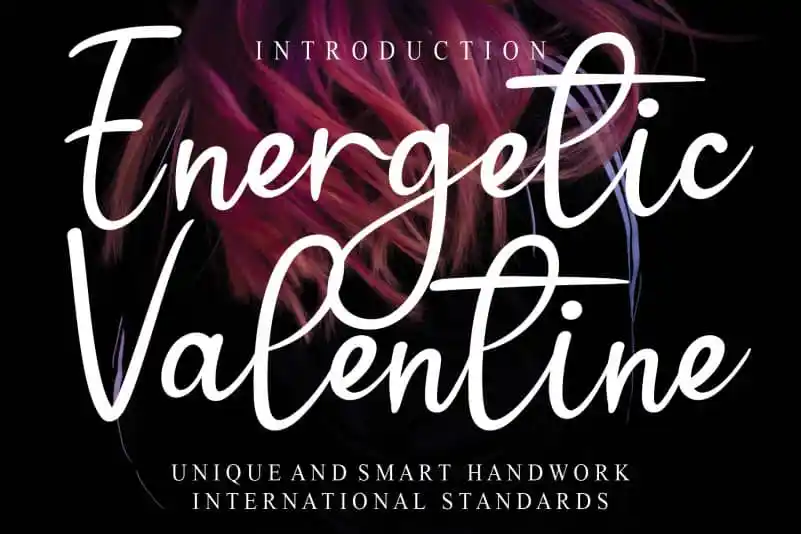
Energetic Valentine Script Font – Download Grátis
Esta é uma fonte de traçado para cartões de aniversário, chamada ‘Energetic Valentine Script Font’, criada pelo designer creativeletter. Ela oferece um visual elegante e moderno que pode ser usada para criar cartões personalizados de amor com o toque especial dos tempos atuais. Suas letras fluidas e vibrantes refletem a energia apaixonada do Valentine’s Day, combinando clássico romance com uma nova dinâmica estilizada. Esta fonte não apenas é perfeita para criar cartões de aniversário encantadores, mas também se destaca como um recurso gráfico versátil para o seu projeto de design. Sempre em busca de oferecer um produto que surpreenda e inspire, a ‘Energetic Valentine Script Font’ está aqui para tornar cada projeto único e especial.